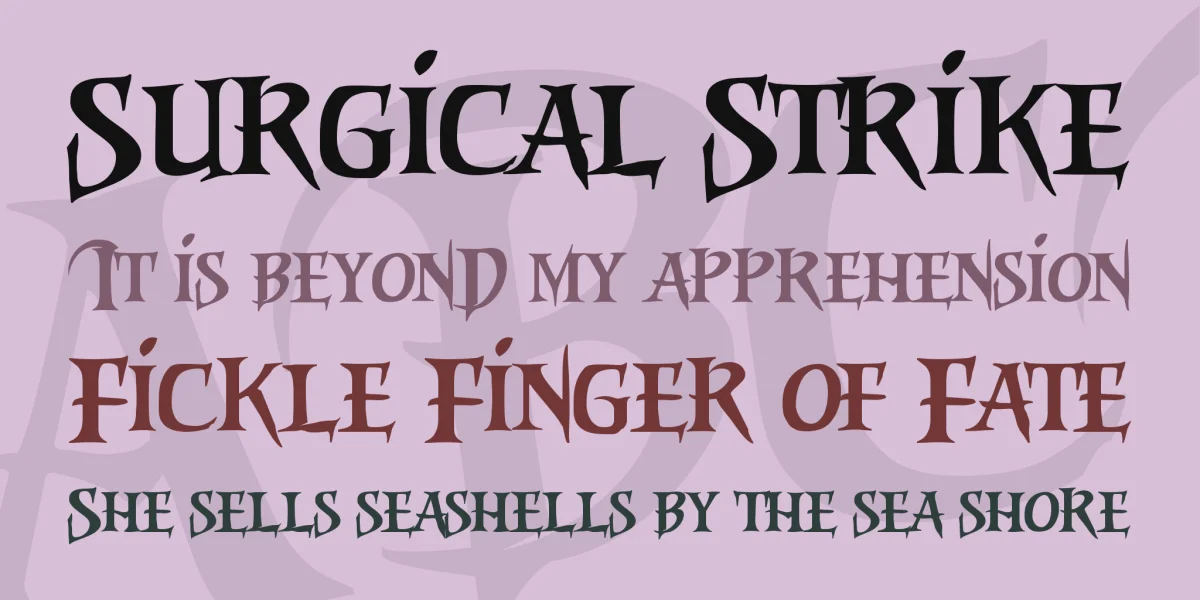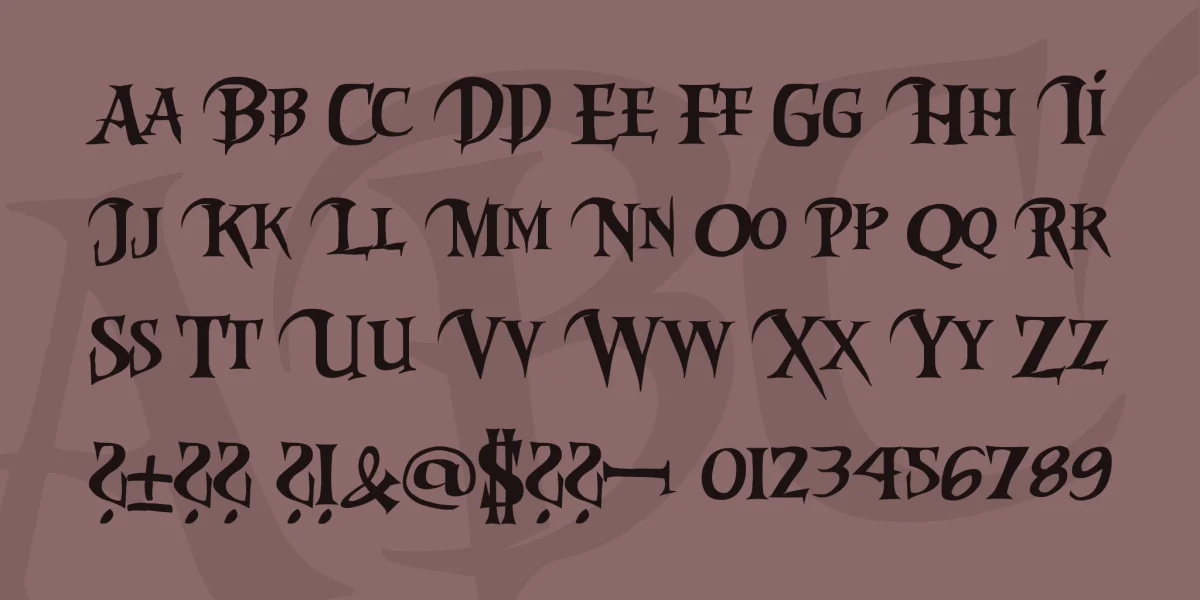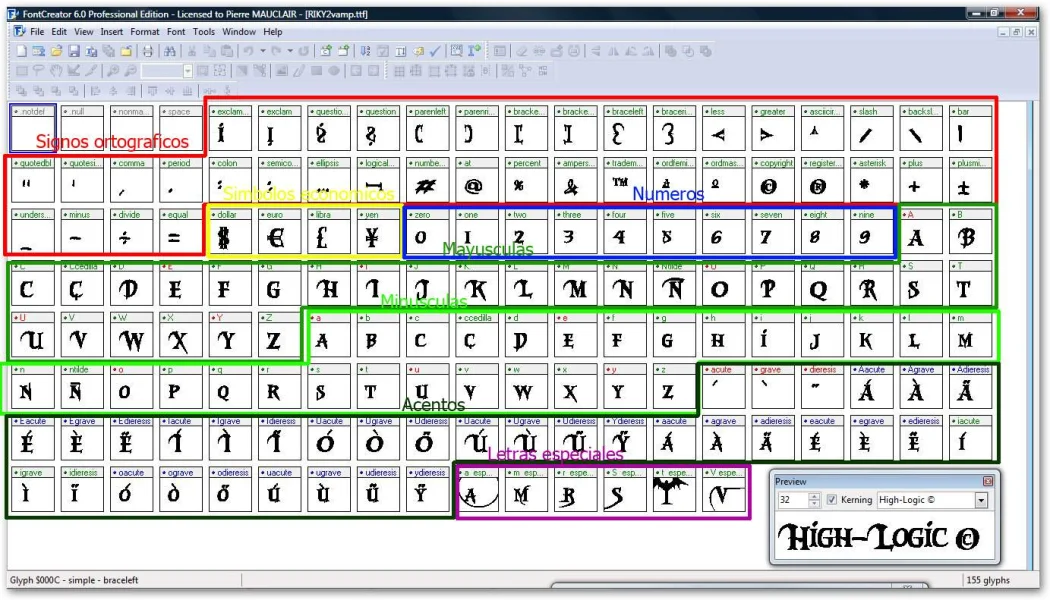
La Fuente RIKY VAMPDATOR es una tipografia ya existente pero esta modificada y adaptada. Pertenece a la gran familia de las fuentes decorativas. Su uso es ideal para los diseñadores que utilizan Photoshop o algún otro programa de retoque o edición de imagen, ya que esta fuente da un toque muy llamativo a los documentos.
Su nombre original es Evil Dead 3 DEMO y la versión desde la que se ha creado es 1.0 DEMO y esta creada por Thomas W. Otto para Norfok Inc.
Es más legible con grandes tamaños debido a su complicado contorno (tamaños superiores a los 18 puntos).
Principalmente fue utilizada para crear el titulo de un clan de vampiros que funde en el Bitefight Español server 6 (alrededor del 2006), actualmente ese jugador esta bloqueado y me cree una cuenta en Mostergame (un juego de caraceristicas similares, alrededor del 2007).
Ahora he adaptado y modificado la fuente para su facil uso en la creacion del titulo del clan.